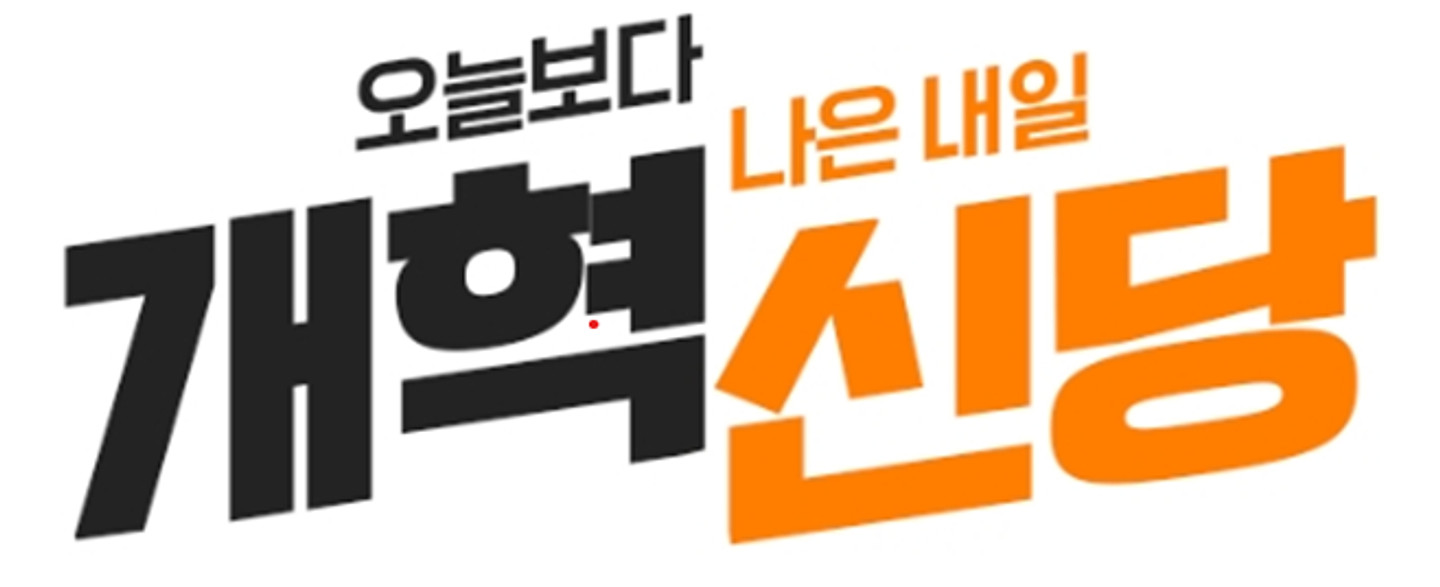
Sandoll 시네마극장, KoreanRKTR Regular 폰트와도 비슷해 보이지만 다른점이 있어 정확하게 어떤 폰트지 찾아주세요!!ㅠㅠ
Sandoll 시네마극장
을 기반으로 변형을 많이 가한 로고인 것 같습니다.
남산양복점
남산양복점인 것 같네요. 위에 글씨는 타이포 풀고딕 쪽인 것 같구요.